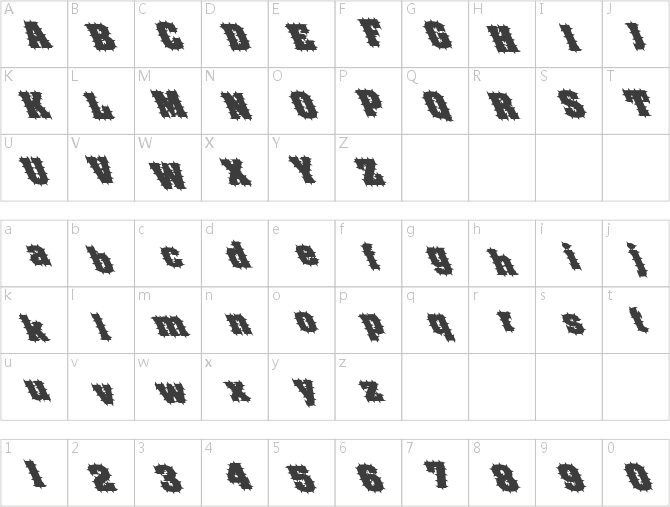
FZ BASIC 52 SPIKED LEFTY
FZ BASIC 52 SPIKED LEFTY介紹
FZ BASIC 52 SPIKED LEFTY字體字庫是一款讓人賞心悅目、百看不厭的英文字體,適合各類廣告和產(chǎn)品包裝設(shè)計應(yīng)用,字體大小0.08MB,格式為ttf字體,上傳用戶是素年錦時,作者/版權(quán)方為未知